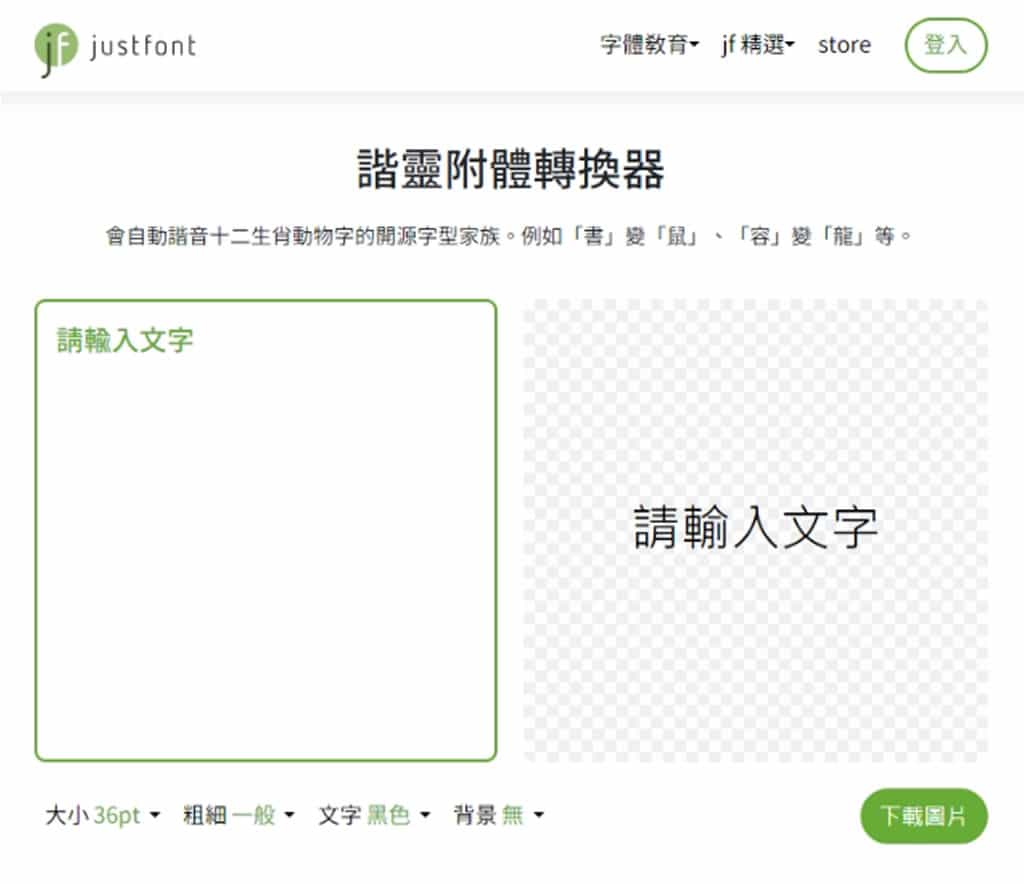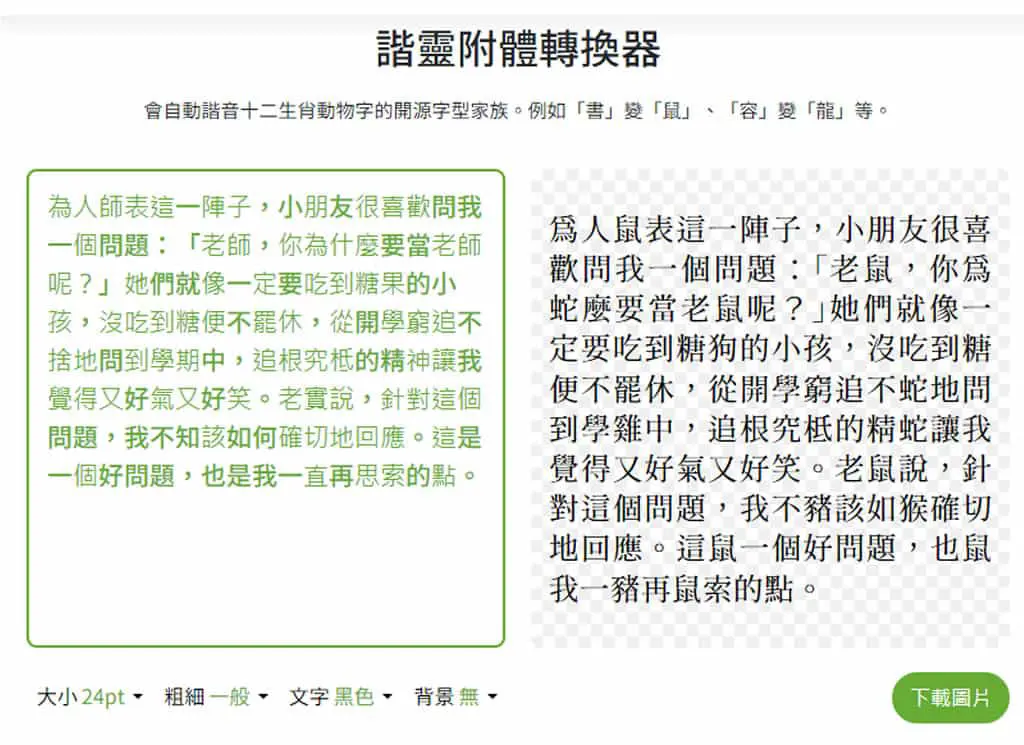
AllPunType 諧靈附體轉換器:免費將文字自動變身為趣味生肖諧音字
「諧靈附體轉換器」是 justfont 推出的免費線上工具,讓使用者可快速將文字轉換成富有創意的十二生肖動物諧音字,例如「書」轉為「鼠」、「容」轉為「龍」等。該轉換器基於 justfont 的「諧靈附體 AllPunType」字型,該字型改編自源流明體,專為呈現近音字的動物諧音效果而設計,並提供多達 7 種字重,滿足各種字體需求。
justfont 網站指出,這款「諧靈附體 AllPunType」字型涵蓋了完整的十二生肖動物,並且支援部分中、英、日文的近音字轉換,使文字更具趣味性和視覺吸引力。此外,該字型採用 SIL Open Font License 1.1 授權,開源且免費下載使用。而透過「諧靈附體轉換器」,使用者可以直接在線上體驗這些有趣的文字效果,無需安裝字型便可快速轉換。
一鍵將文字轉換為十二生肖諧音字!支援中英日語近音字,線上體驗無需下載字型
1.進入「AllPunType 諧靈附體」轉換器網站,可以直接在綠色文字框之中輸入中文文字。
2.碰到諧音字會自動轉換,可以來看看官網所給出的動畫展示。
3.以一段文字來測試。
在文字框的底部,還可以調整文字大小、粗細、顏色及選擇有無背景,最終成品,可以點擊「下載圖片」取得。
無論是安裝「AllPunType 諧靈附體」字型,還是在線上使用諧靈附體轉換器,都可輕鬆將文字轉換成趣味十足的十二生肖諧音字,讓創作更具特色和趣味性。